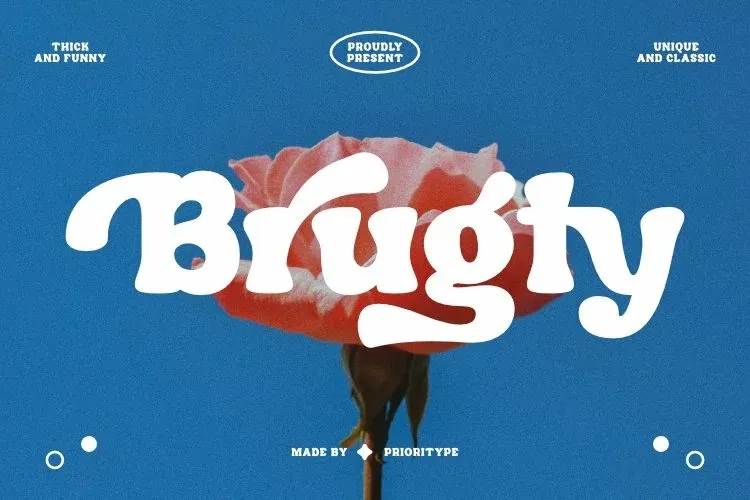
A fonte Brugty é inspirada nas belas ilustrações vintage dos anúncios, com mais de 100 caracteres alternativos que a tornam uma opção divertida e única para projetos gráficos. Ela foi criada pelo designer font Prioritype em 99designs. Esta fonte oferece um toque retro inusitado ao seu design, enquanto ainda mantém sua elegância clássica perfeita para aplicação em anúncios publicitários ou qualquer outro tipo de projeto visual. Engajante e versátil, a Brugty pode ajudar você a destacar seus projetos visuais com um toque memorável do passado.